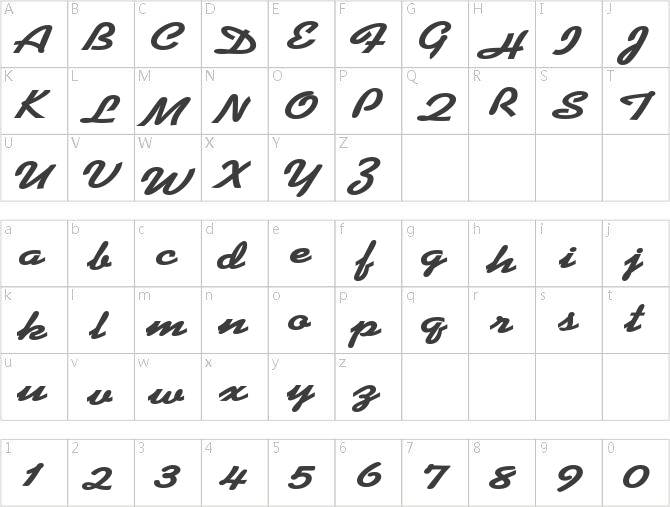
DinerScriptExtended-Bold
DinerScriptExtended-Bold介紹
DinerScriptExtended-Bold字體字庫是一款讓人賞心悅目、百看不厭的英文字體,適合各類廣告和產品包裝設計應用,字體大小0.05MB,格式為ttf字體,上傳用戶是Apple,作者/版權方為未知